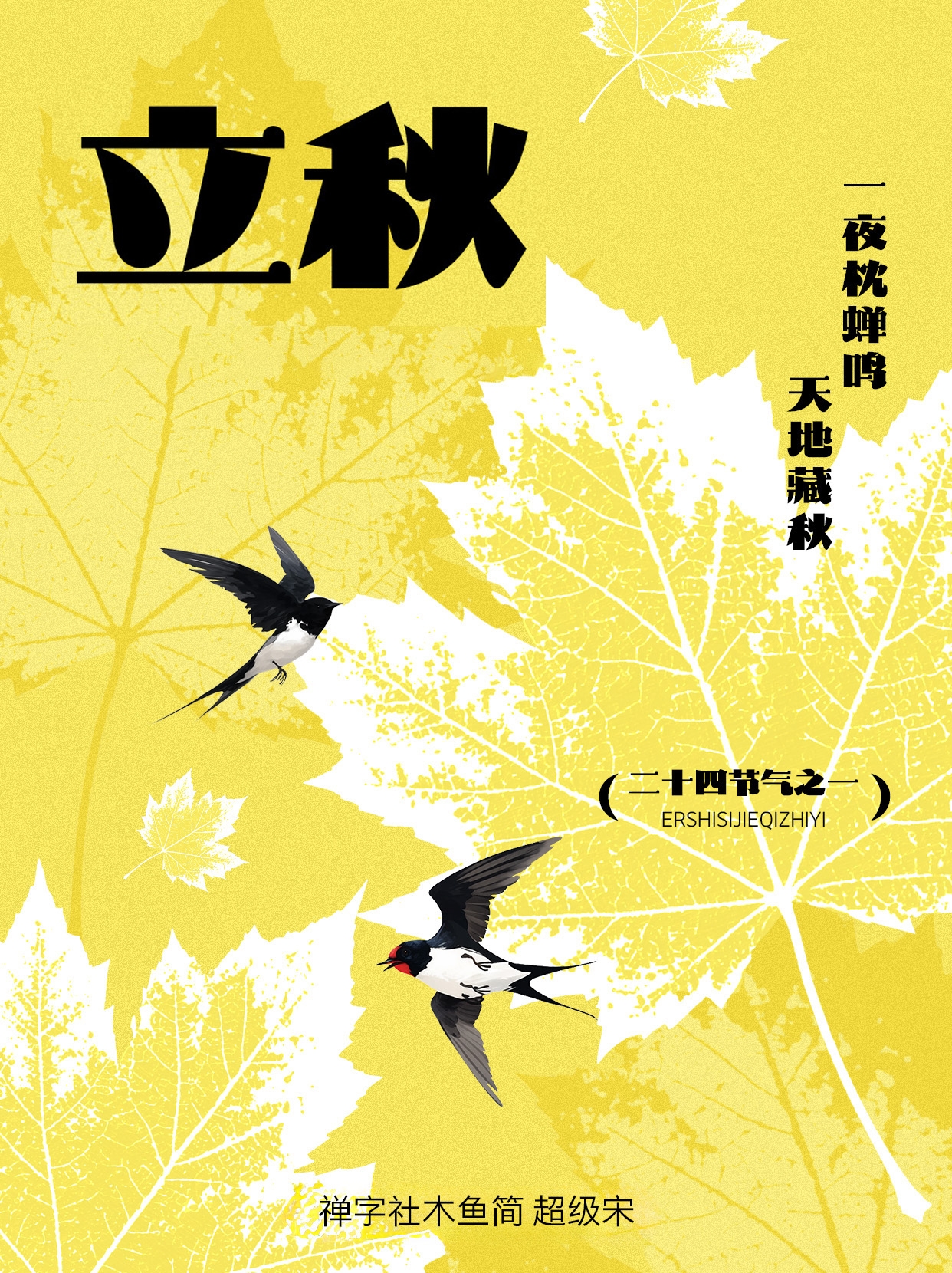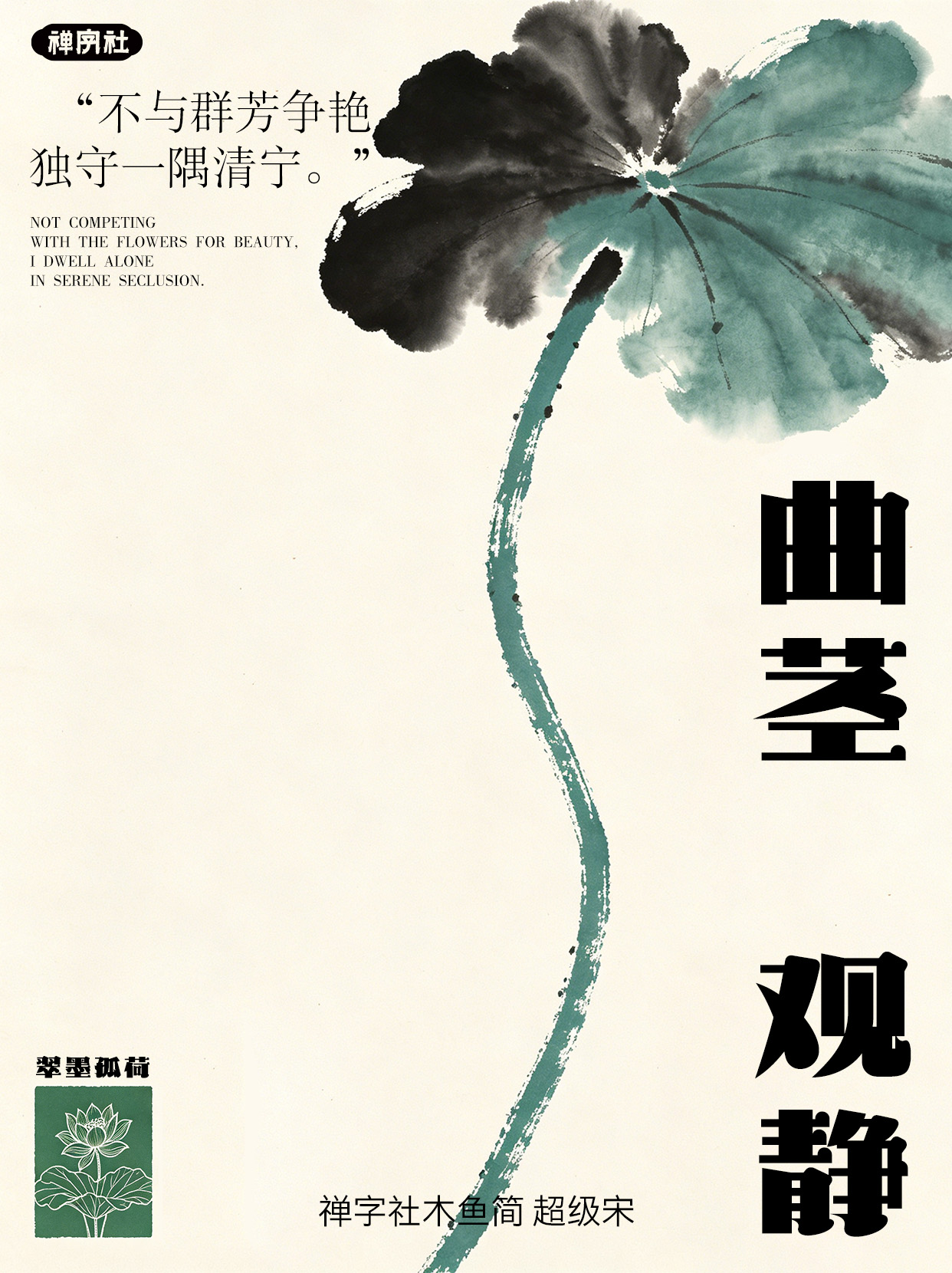
禅字社木鱼简 超级宋
禅字社木鱼简 超级宋是一款字型宽扁、中宫较大的字体,将圆弧、圆角特点融入扁宽的宋体中,使其凸显字体的圆润饱满感。横笔画收笔采用半圆形状,转折处运用圆弧的处理方式,使其整体更加饱满和统一。横细竖粗对比强烈。勾笔在转折处做出头圆弧,内收如同 “砚台”形状,使其字体更加稳重且具备特色。